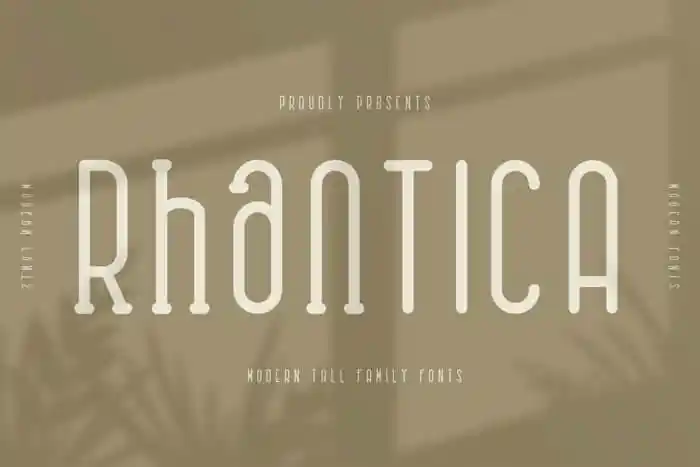
Rhantica Display Font – Download Grátis
A Rhantica Display é uma linda fonte de exibição que combina perfeição de contorno com duas estilos únicos – Regular e Serif. Essa fonte não apenas oferece elegância, mas também uma alma vibrante e ativa, ao mesmo tempo em que respeita suas regras e limitações formais. É um exemplo da geometria clara e estruturada de Crump Hand, o designer original deste tipo de fonte. A Rhantica Display é capaz de criar um impacto imediato, perfeitamente adaptável a textos em grande escala para aplicativos de mídia social, materiais gráficos e design editorial. Seu formato linhas pontilhadas permite que você personalize ainda mais o seu design, oferecendo uma alternativa elegante para qualquer texto semelhante. Com sua versão linha-dinâmica complementar, a Rhantica Display pode moldar elementos de forma minimalista e precisa, ao mesmo tempo em que se destaca como um elemento gráfico independente. É perfeita para designers gráficos que valorizam uma combinação assertiva de formas geométricas e nuances mais suaves. Este tipo de fonte é perfeito para quem busca uma fonte de exibição ideal para apresentar conteúdo em ambientes digitais, garantindo uma experiência visual envolvente e harmoniosa.